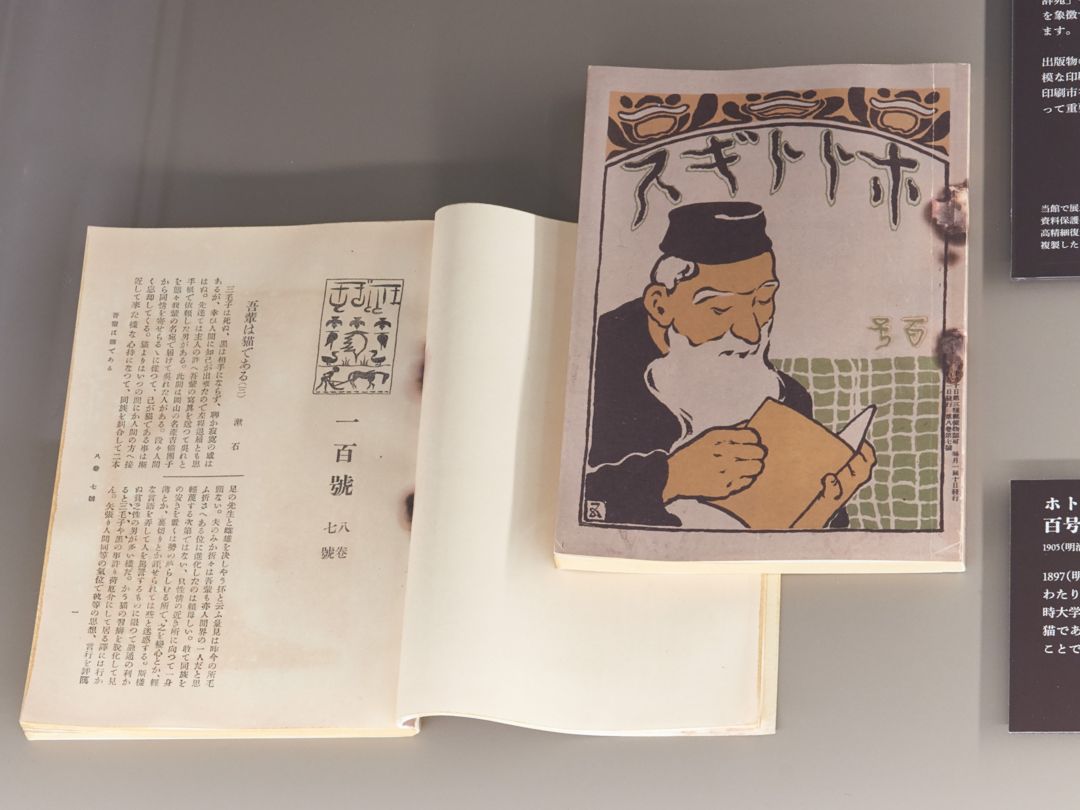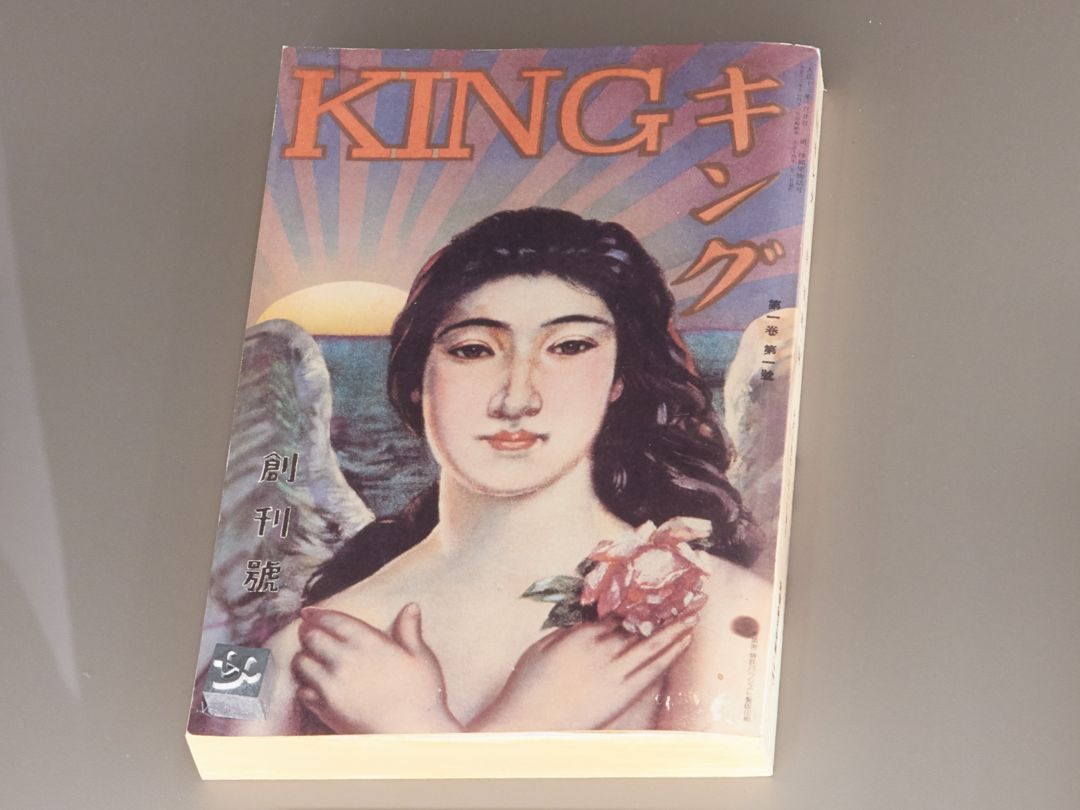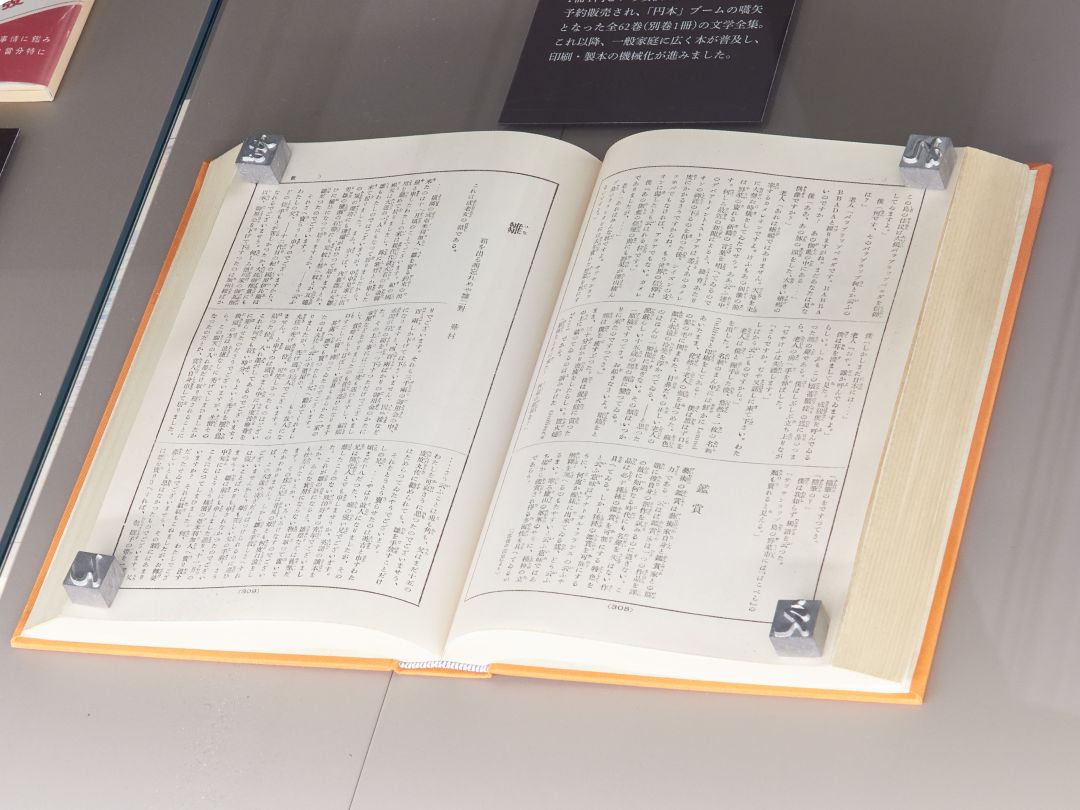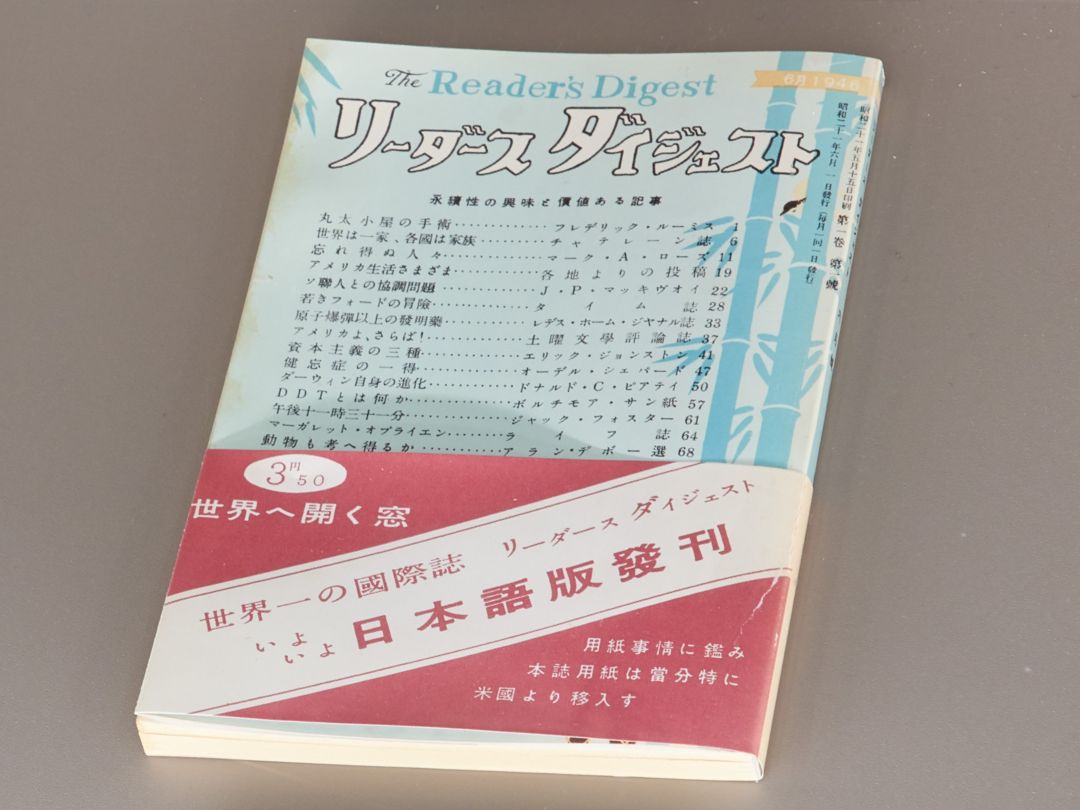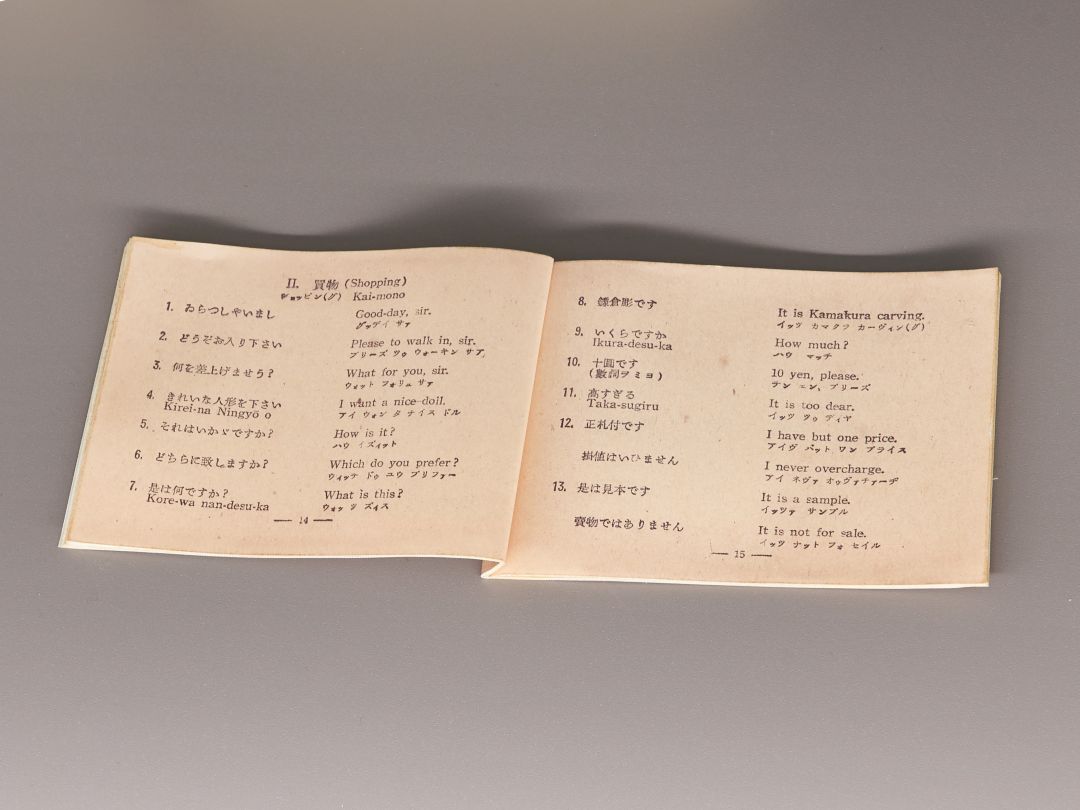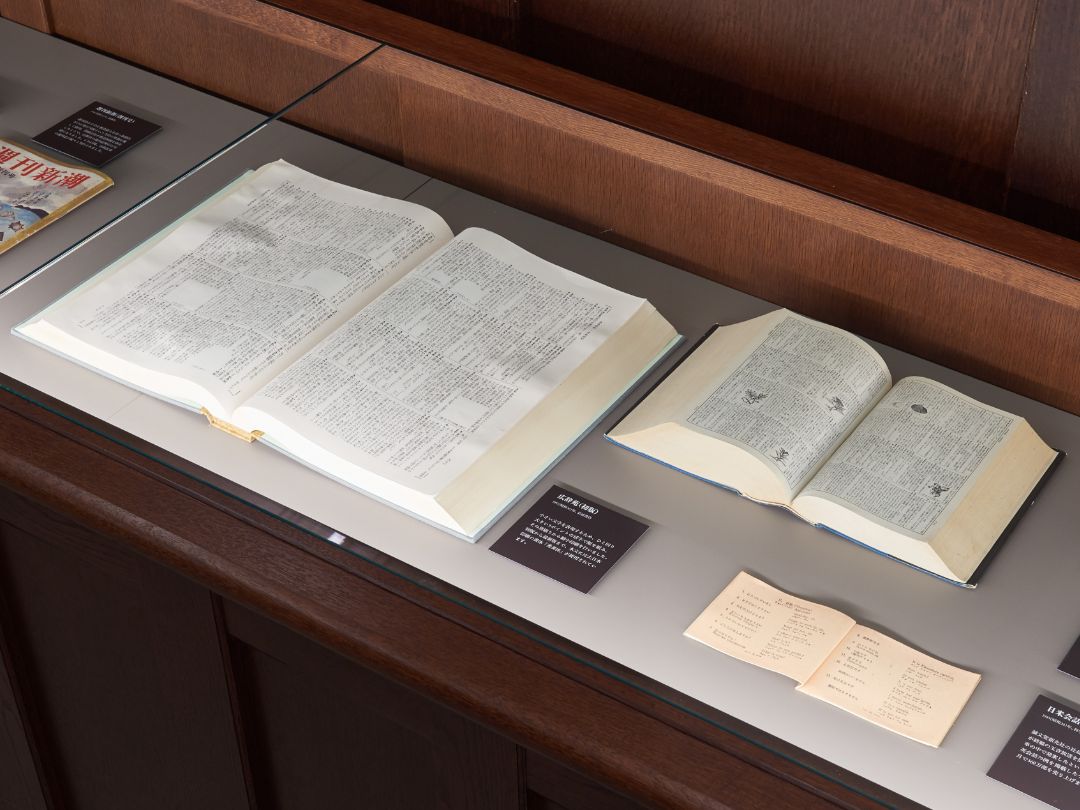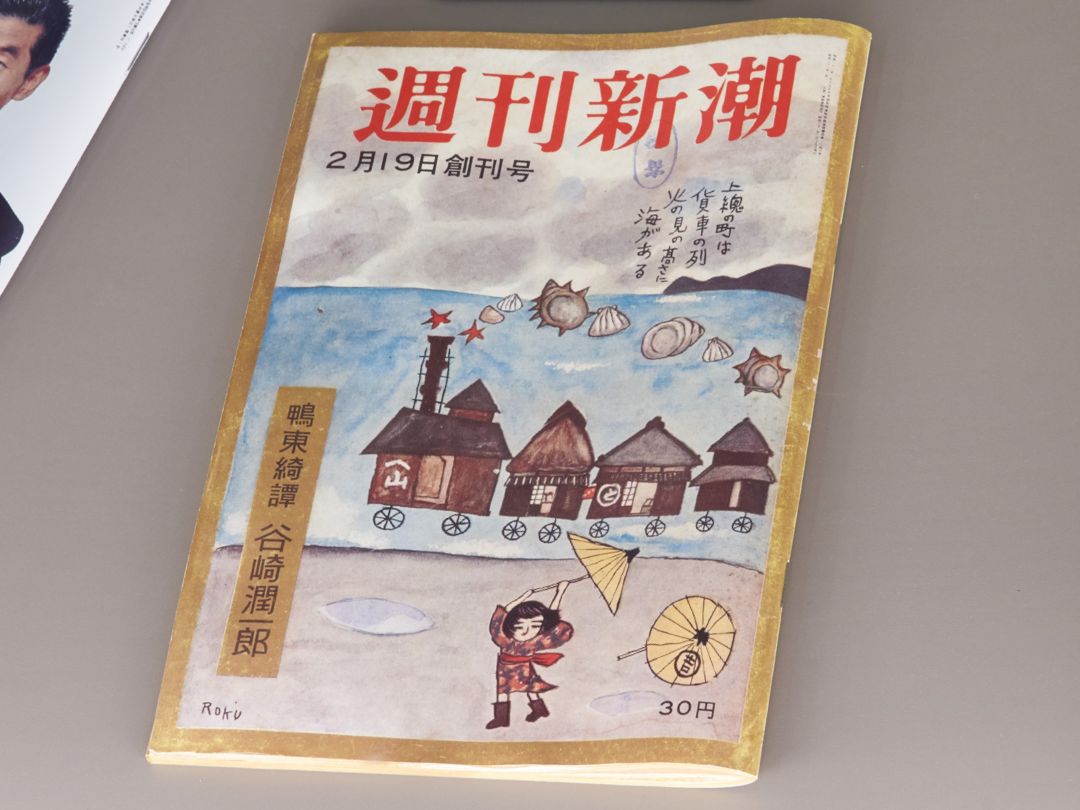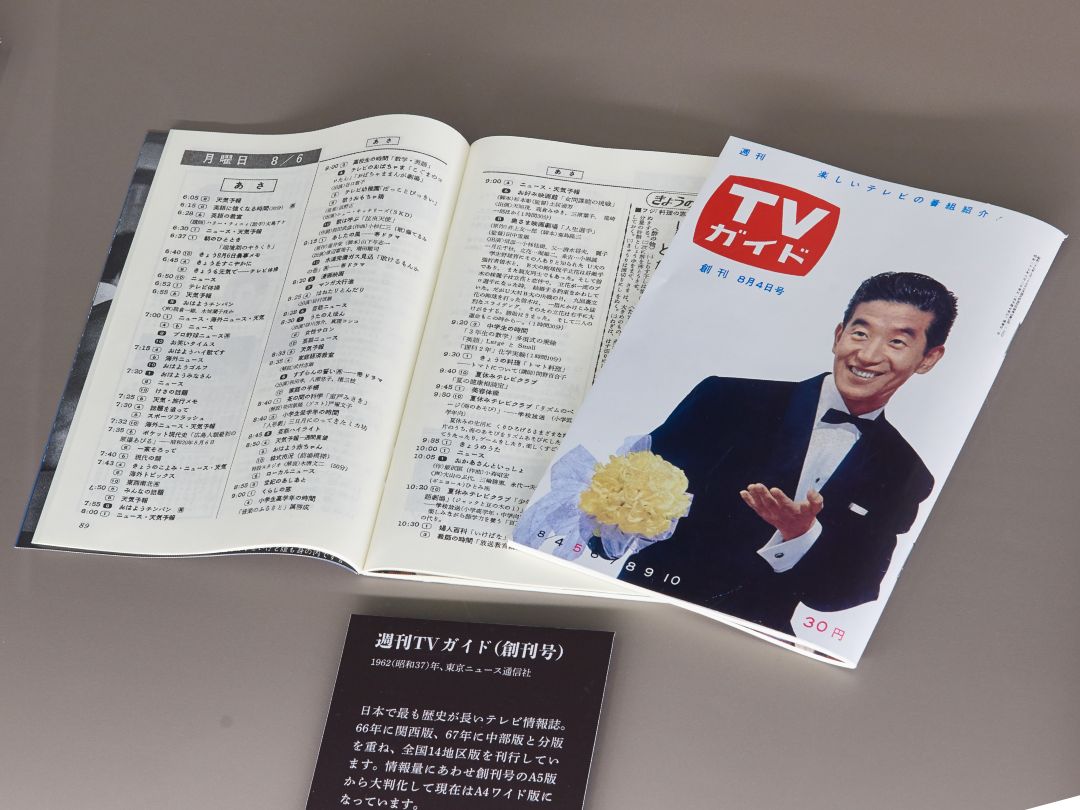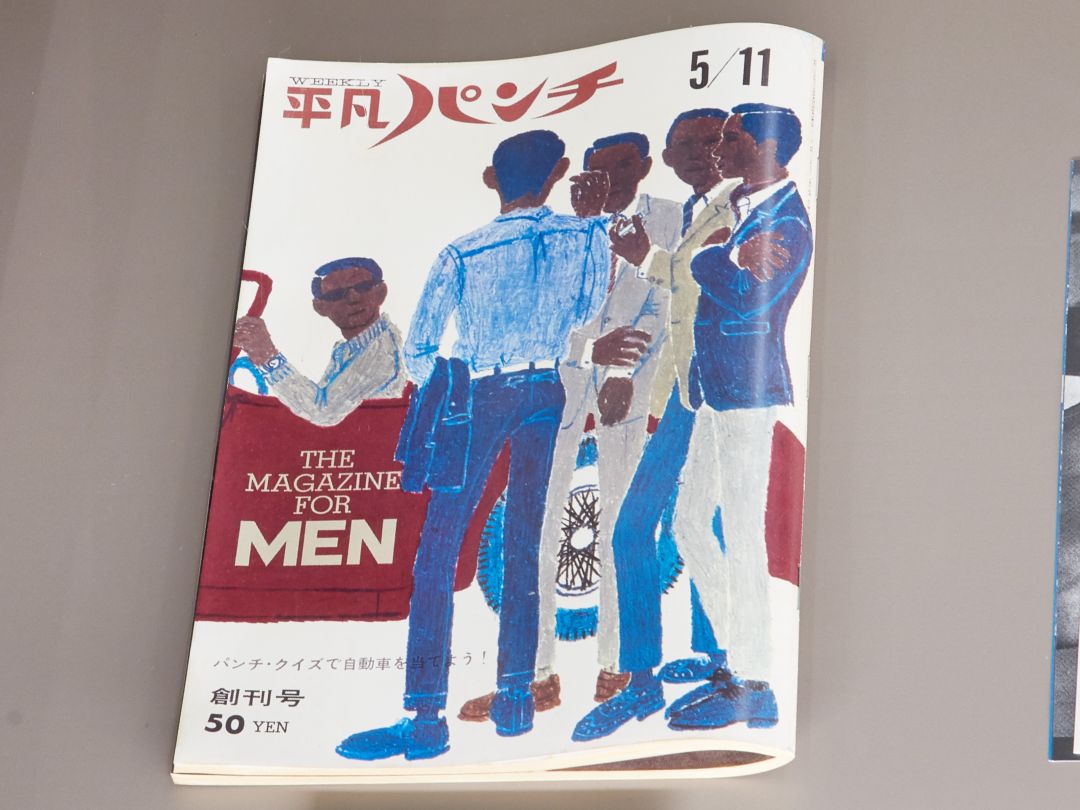
大日本印刷がつくった
本や雑誌
市谷工場では、100年以上前から膨大な数の本や雑誌がつくられてきました。その中には、夏目漱石を世に送り出すことになる俳句雑誌の「ホトトギス」や、日本を代表する辞書のひとつ「広辞苑」をはじめ、歴史に残る本や時代を象徴する雑誌などが多く含まれています。
出版物の大量発行には、首都圏の大規模な印刷設備は不可欠でした。大日本印刷市谷工場は、日本の出版流通にとって重要な役割を果たしてきたのです。
当館で展示している紙資料は、資料保護の観点から高精細復元技術(プリモアート®)で複製したものです。
ホトトギス
百号八巻七号、1905(明治38)年、ほとゝぎす発行所
1897(明治30)年に創刊。120年以上にわたり出版を続けている俳句雑誌。当時大学講師だった夏目漱石が『吾輩は猫である』『坊っちゃん』を発表したことでも知られています。
キング
創刊号、1925(大正14)年、大日本雄弁会講談社
日本で初めて発行部数100万部を超えた大衆雑誌。エピソード中心の立身出世物語や道徳的訓話など、バラエティ豊かな読み物を手軽に楽しめる編集方針は、多くの読者を引きつけました。
現代日本文学全集 芥川龍之介集
1928(昭和3)年、改造社
1冊1円という安価で1926(大正15)年に予約販売され、「円本」ブームの嚆矢となった全62巻(別巻1冊)の文学全集。これ以降、一般家庭に広く本が普及し、印刷・製本の機械化が進みました。
リーダーズ・ダイジェスト(日本語版・創刊号)
1946(昭和21)年、日本リーダーズ・ダイジェスト社
米国の人気月刊誌『リーダーズ・ダイジェスト』の日本語版が創刊され、大日本印刷は英語版とともに印刷を受注。日本語版の発行部数は一時130万部に上りました。
日米会話手帳
1945(昭和20)年、科学教材社
誠文堂新光社の小川菊松社長(当時)が終戦の玉音放送を聞き、上京する汽車の中で発案したという英会話指南書。英会話79例を掲載した小冊子で、3カ月で360万部を売り上げました。
広辞苑(初版)
1955(昭和30)年、岩波書店
小さい文字を表現するため、ひと回り大きい9ポイントの活字で版を組み、その清刷りから縮小印刷を行いました。初版から最新版まで、本文には大日本印刷の書体「秀英体」が使用されています。
週刊新潮(創刊号)
1956(昭和31)年、新潮社
週刊誌は十分な製造能力を持つ新聞社だけが発行可能という当時の常識を覆して創刊。印刷会社が製造体制を強化したことで、出版社の週刊誌発行が可能になりました。これ以降、出版社系の週刊誌が続々と刊行されました。
週刊TVガイド(創刊号)
1962(昭和37)年、東京ニュース通信社
日本で最も歴史が長いテレビ情報誌。66年に関西版、67年に中部版と分版を重ね、全国14地区版を刊行しています。情報量にあわせて創刊号のA5版から大判化して現在はA4ワイド版になっています。
週刊平凡パンチ(創刊号)
1964(昭和39)年、平凡出版
週刊誌創刊ブームの流れの中で創刊。ターゲットを明確にした雑誌の創刊が相次ぐなか、特にファッショナブルな成年男子を引きつけ、カルチャー雑誌の草分けとなりました。